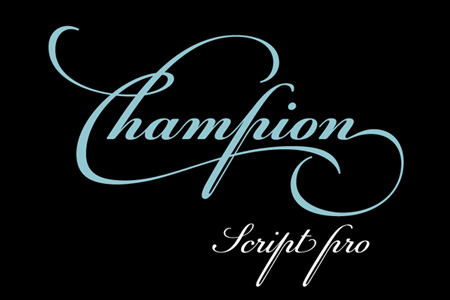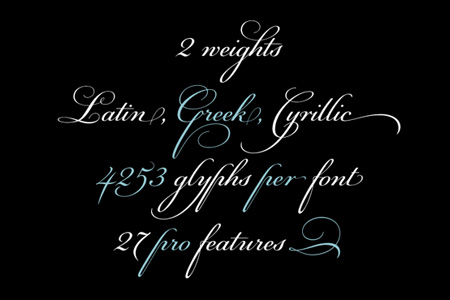
PF Champion Script Pro (Parachute)
PF Champion Script Pro is the most advanced and powerful script
ever made. It is based on the manuscripts of one of the great writing
masters of the 18th century Joseph Champion. There are many
reasons that make PF Champion Script Pro so unique. Each one
of the 2 weights is loaded with the amazing number of 4253 glyphs,
offering simultaneous support for all European languages based on
the Latin, Greek and Cyrillic scripts.
da sind schöne Buchstaben dabei. Was meiner bescheidenen Meinung nach gar nicht geht sind das "C" und das "p" aus dem Beispiel.
Mit dem C hab ich keinerlei Probleme. Das p ist tatsächlich
etwas gewöhnungsbedürftig aber in dieser Form in vielen Ländern
gebräuchlich. Schade das es keine alternatives p gibt ...
Das C aus dem "Cyrillic" meinte ich. Das sieht sehr gestaucht aus.
Das sieht nach jeder Menge Arbeit aus.
Klasse Formen - besonderes die Rahmen und schwungvollen Kleinbuchstaben habens mir angetan.
Weniger gut gelungen finde ich ebenfalls das (gestauchte) C und p, und das f. Wahrscheinlich auch deshalb, weil wir heute hier einfach eine andere Schreibweise gewohnt sind. Ansichtssache.
Was mir noch gerade auffällt: die Ziffern mag ich auch nicht. Zumindest 2, 5 und 7 wirken irgendwie unharmonisch — ohne dass ich sagen könnte, warum.
Weniger gut gelungen finde ich ebenfalls das (gestauchte) C und p, und das f. Wahrscheinlich auch deshalb, weil wir heute hier einfach eine andere Schreibweise gewohnt sind.
Die Grundform des p finde ich gar nicht schlecht. Es hat nur im Vergleich zu anderen Buchstaben zu viel Schwere.